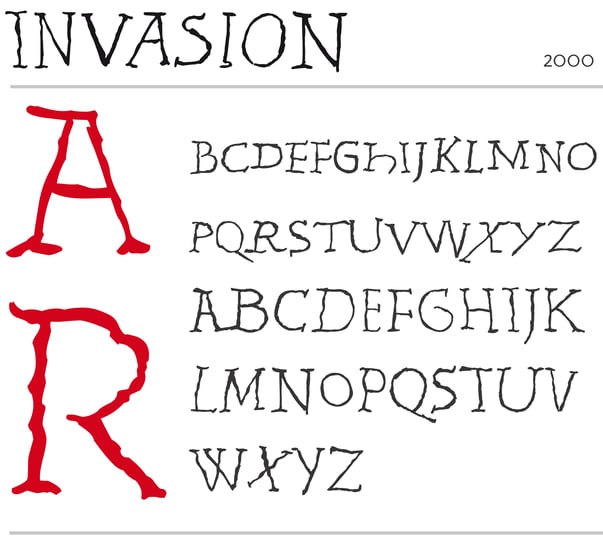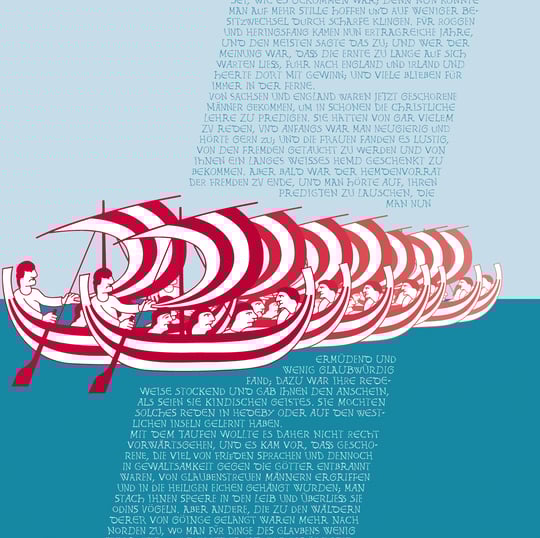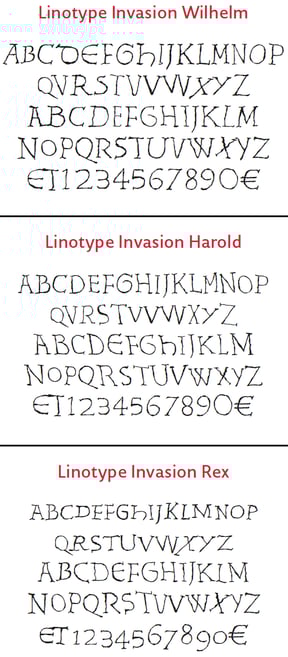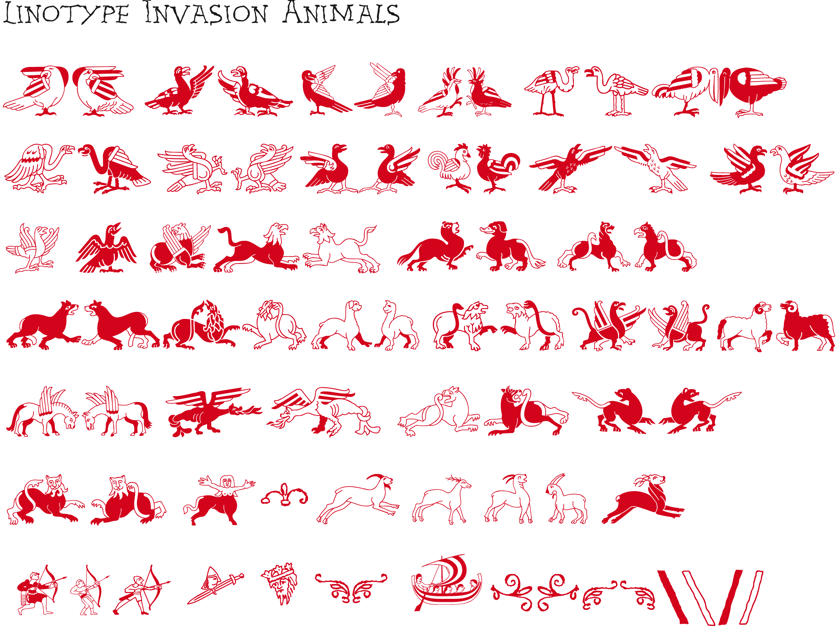
Linotype Invasion
Im Jahre 1066 segelte Wilhelm, Herzog der Normandie, mit einer großen Flotte nach England, um die ihm versprochene Königskrone zu erobern. In der Schlacht bei Hastings besiegte er seinen Widersacher Harold, wurde König von England und ging als Wilhelm der Eroberer in die Geschichte ein… Der berühmte Teppich von Bayeux aus dem 11. Jahrhundert erzählt in einer Bildergeschichte vom Kampf Wilhelms. Der lateinische Text erläutert die Szenen in kurzen Sätzen. Beim Lesen eines Artikels über »verratzte« Szene-Typografie kam mir die Idee, die gestickte Schrift des Teppichs in eine Drucktype umzusetzen. Dabei entstanden dann drei Sätze von Buchstaben und dazu ein Symbol-Font mit einigen der Tiere und Fabelwesen, die auf dem Teppich dargestellt sind. Die Invasion war im Januar 2003 »Font of the Week«.